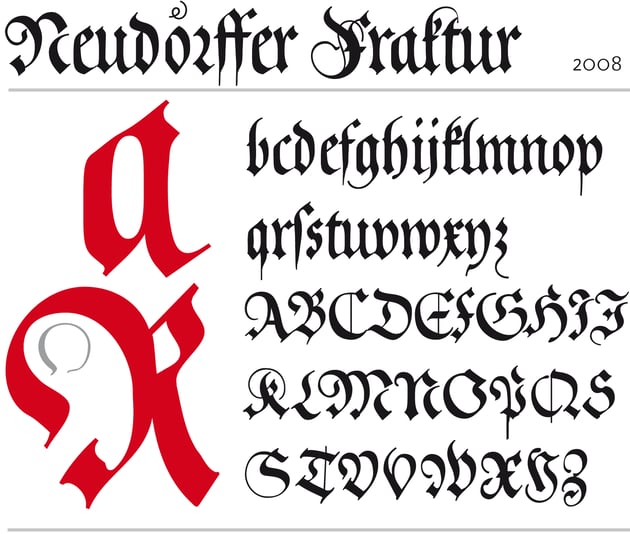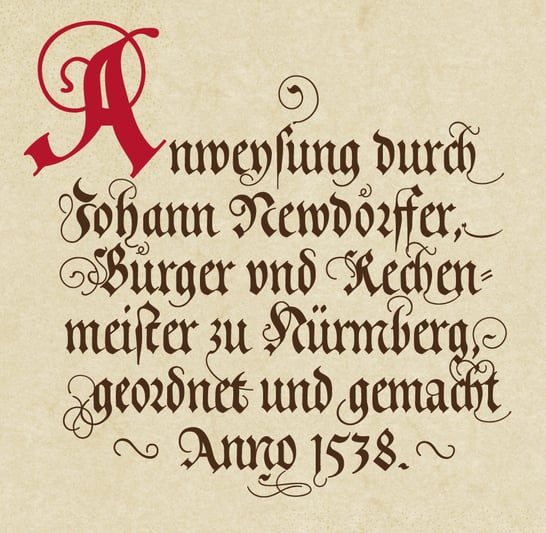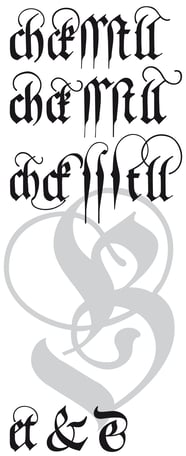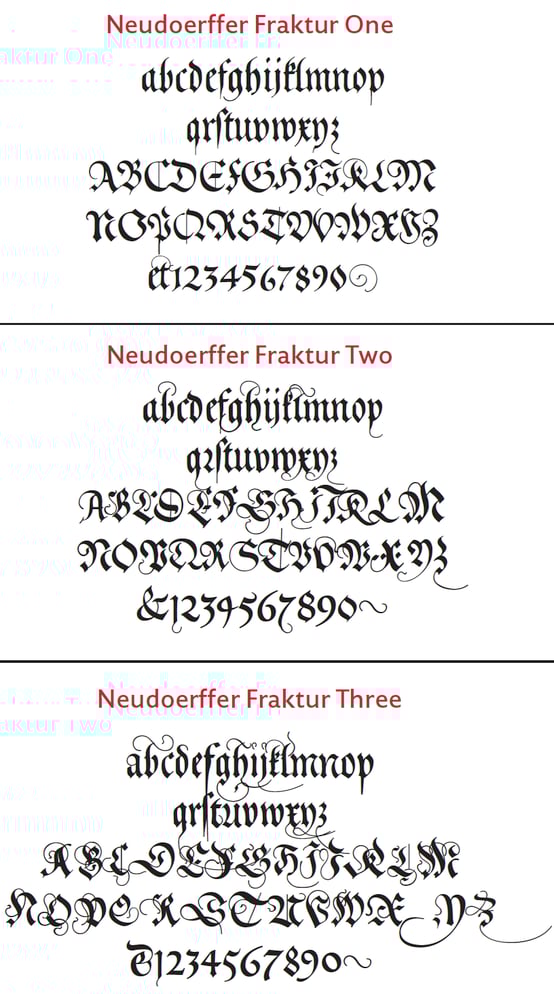
Neudoerffer Fraktur
Seit 1990 habe ich einzelne Buchstaben aus den Schriftmustern des Johann Neudörffer (Nürnberg 1538) umgezeichnet um sie für Schriftzüge zu verwenden. Neudörffers Schriften markieren den Anfang der Fraktur, die dann bei der Theuerdank-Fraktur und der Dürer-Fraktur das erste Mal in Blei gegossen wurde. In seinen „Anweysungen“ zeigt Neudörffer einfache und stark verschnörkelte Formen ebenso wie Ligaturen. Entstanden sind drei Fonts:
One mit einfachen Formen, nahe an einer gedruckten Fraktur.
Two mit stärker verzierten Versalien und Alternativbuchstaben sowie
Three mit stark kalligrafischen Formen.